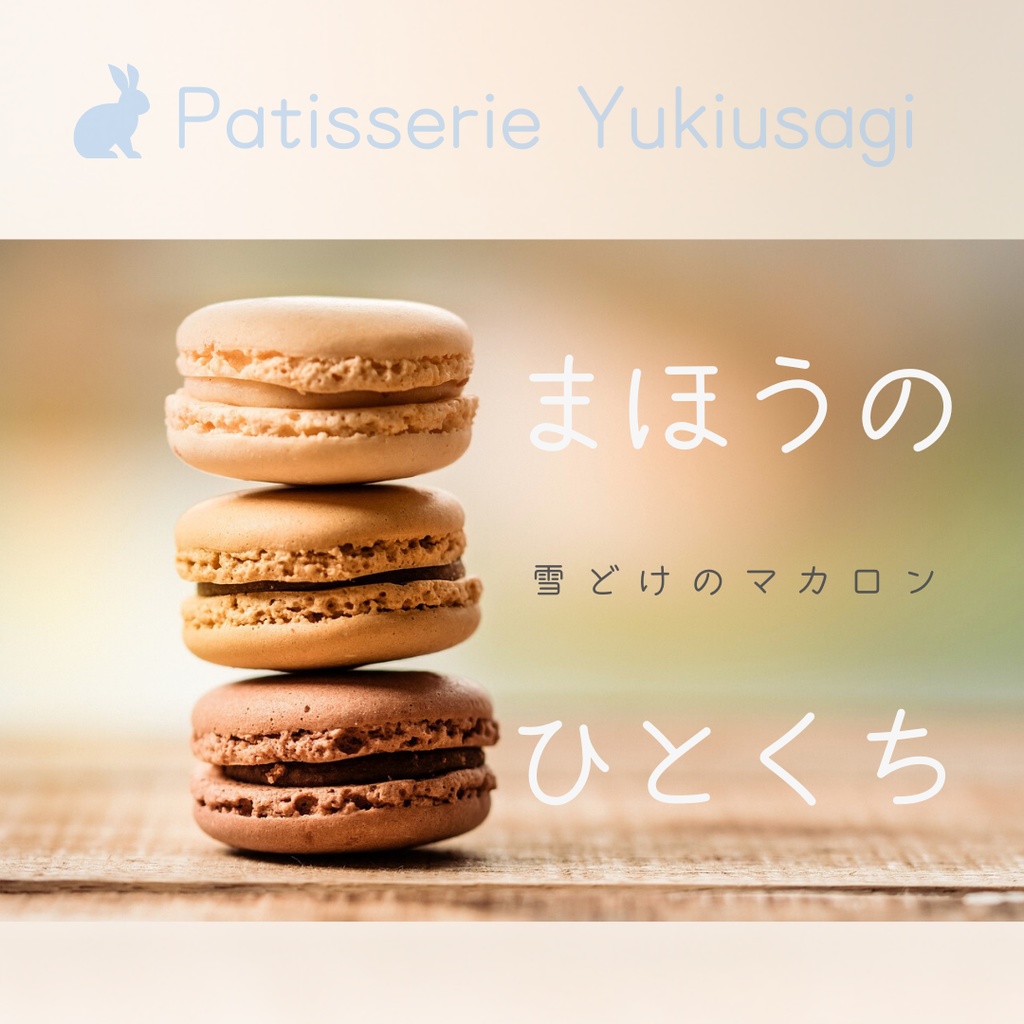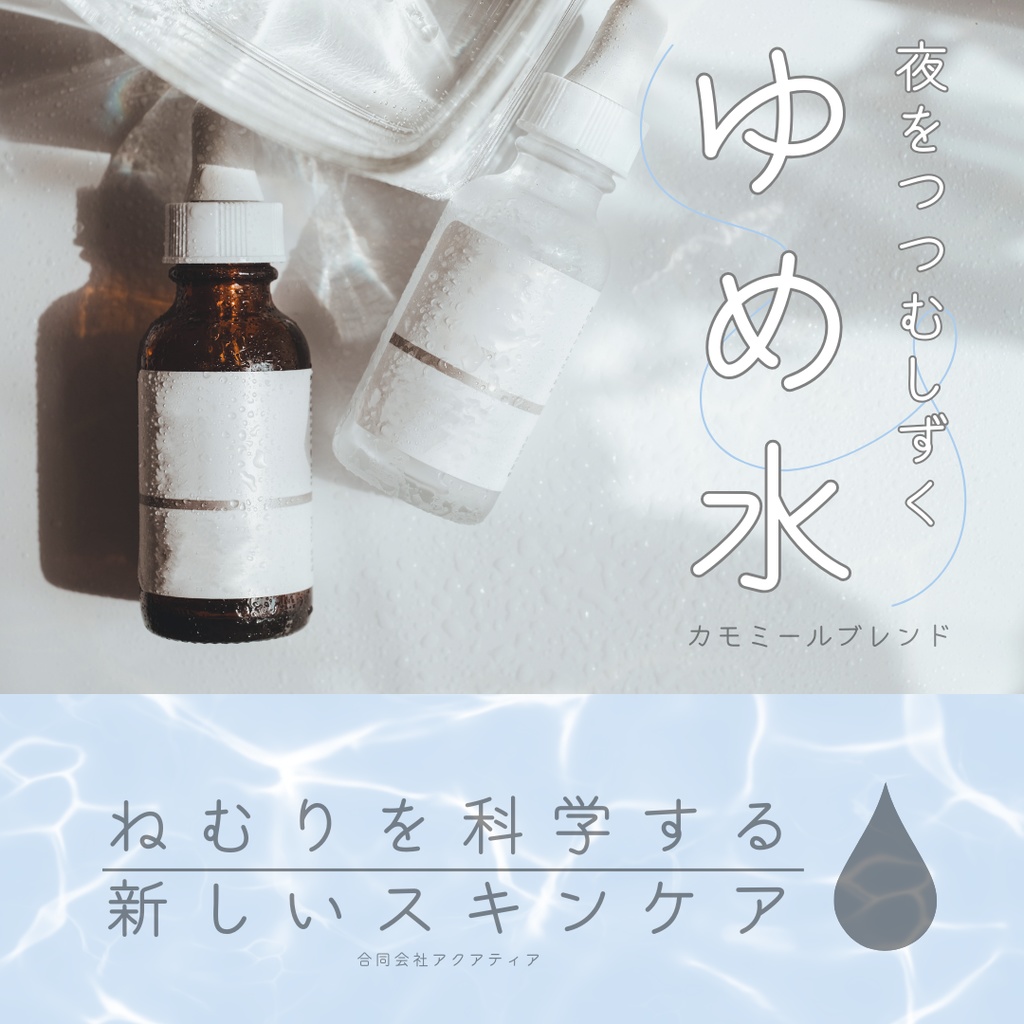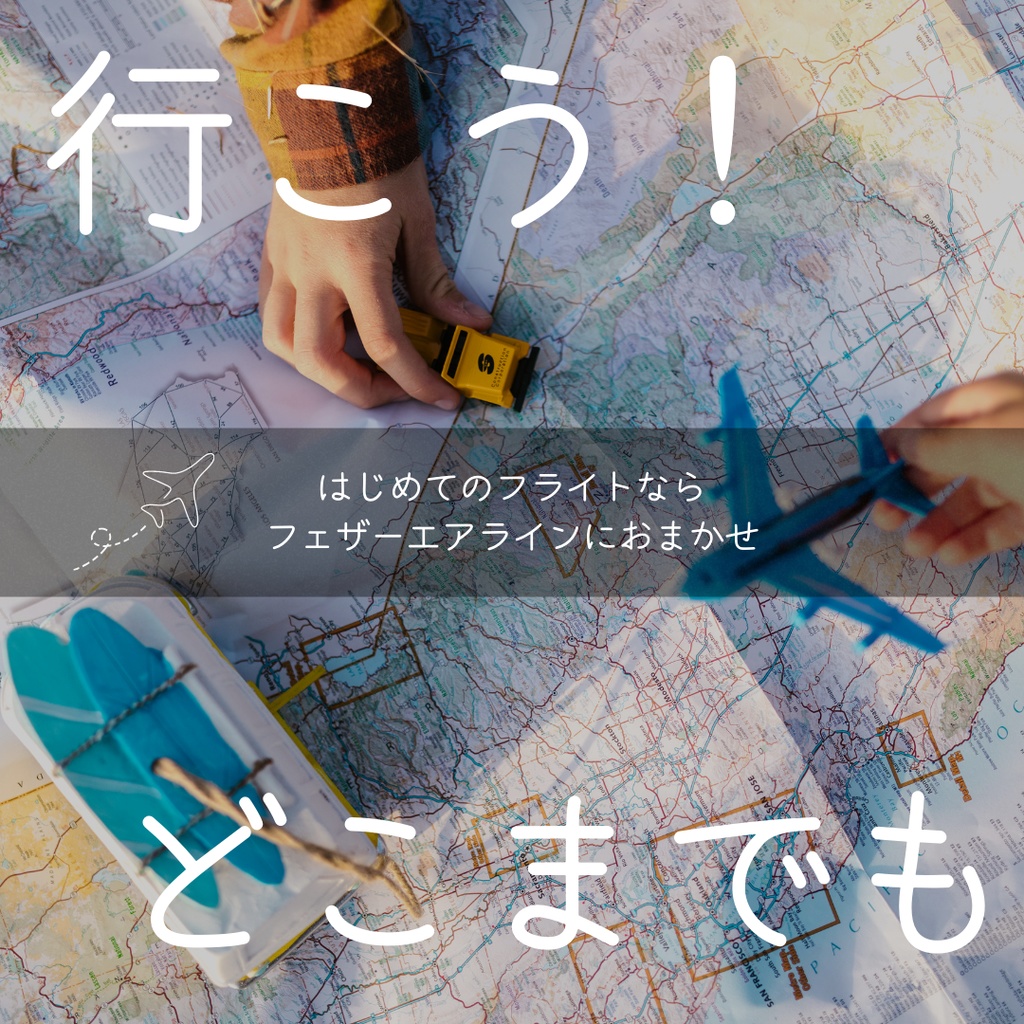
【フリーフォント】くすくすあめ
収録文字
◼︎概要 ・全角ひらがな ・全角カタカナ ・漢字(小学1〜2年生で習うもの) ・半角英数字 ・全角英数字 ・約物 ◼︎文字一覧 あいうえおかきくけこさしすせそたちつてとなにぬねのはひふへほ まみむめもやゐゆゑよらりるれろわをんゔがぎぐげござじずぜぞ だぢづでどばぱびぴぶぷべぺぼぽぁぃぅぇぉゕゖっゃゅょゎゝゞ アイウエオカキクケコサシスセソタチツテトナニヌネノハヒフヘホ マミムメモヤヰユヱヨラリルレロワヲンヴガギグゲゴザジズゼゾ ダヂヅデドバパビピブプベペボポァィゥェォヵヶッャュョヮヽヾ ⼀右⾬円王⾳下⽕花⾙学気休⽟⾦九空⽉⽝⾒五⼝校左三⼭四⼦⽷字 ⽿七⾞⼿⼗出⼥⼩上森⼈⽔正⽣⻘⽯⾚先千川早草⾜村⼤男⽵中⾍町 天⽥⼟⼆⽇⼊年⽩⼋百⽂本名⽊⽬⼣⽴⼒林六引⽻雲園遠⻩何夏家科 歌画会回海絵外⾓楽活間丸岩顔帰汽記⼸⽜⿂京強教近兄形計元原⾔ 古⼾午後語交光公⼯広考⾏⾼合国⿊今才細作算姉市思⽌紙寺時⾃室 社弱⾸秋週春書少場⾊⾷⼼新親図数星晴声⻄切雪線船前組⾛多太体 台⾕知地池茶昼朝⻑⿃直通弟店点電冬⼑東当答頭同道読内南⾁⾺買 売⻨半番⽗⾵分聞⽶歩⺟方北妹毎万明鳴⽑⾨夜野⽮友曜⽤来理里話 abcdefghijklmnopqrstuvwxyzABCDEFGHIJKLMNOPQRSTUVWXYZ0123456789 abcdefghijklmnopqrstuvwxyzABCDEFGHIJKLMNOPQRSTUVWXYZ0123456789 ,.'"!?+-~//*#&@%;:_()<>[]{}、。’”!?+ー〜/*#&@%;:_()<>「」『』・…○●☆★♡♥♪ ◼︎縦書き対応の全角文字 ぁぃぅぇぉゕゖっゃゅょゎァィゥェォヵヶッャュョヮ、。_ー〜()「」『』